Einführung
Fonts – sie sind wie Kleidung für dein Design. Du kannst ein Outfit haben, das total zusammenpasst, oder eins, das total daneben ist. Genauso ist es bei Schriftarten. Die richtige Kombination kann deinem Text Eleganz, Lesbarkeit und Persönlichkeit verleihen, während falsche Paare chaotisch und unprofessionell wirken.
In diesem Artikel zeige ich dir, wie du Schriftarten kombinierst, welche Paare besonders gut harmonieren und welche Tools dir helfen können, das perfekte Match zu finden. Egal, ob du Flyer, Websites oder Social-Media-Posts gestaltest – hier bekommst du alles, was du brauchst.
Warum Schriftarten zusammenpassen wichtig ist
Stell dir vor, du liest einen Text, bei dem die Überschrift in einer fetten, verschnörkelten Schrift steht und der Fließtext in einer dünnen, unruhigen Schrift. Unangenehm, oder? Genau deshalb ist die Kombination von Schriftarten so entscheidend.
Die richtige Pairing sorgt dafür:
- Lesbarkeit: Dein Text ist leicht zu erfassen.
- Hierarchie: Leser wissen sofort, was wichtig ist (z. B. Überschriften vs. Fließtext).
- Stil & Stimmung: Serifenschriften wirken klassisch, serifenlose modern. Das Zusammenspiel vermittelt die gewünschte Botschaft.
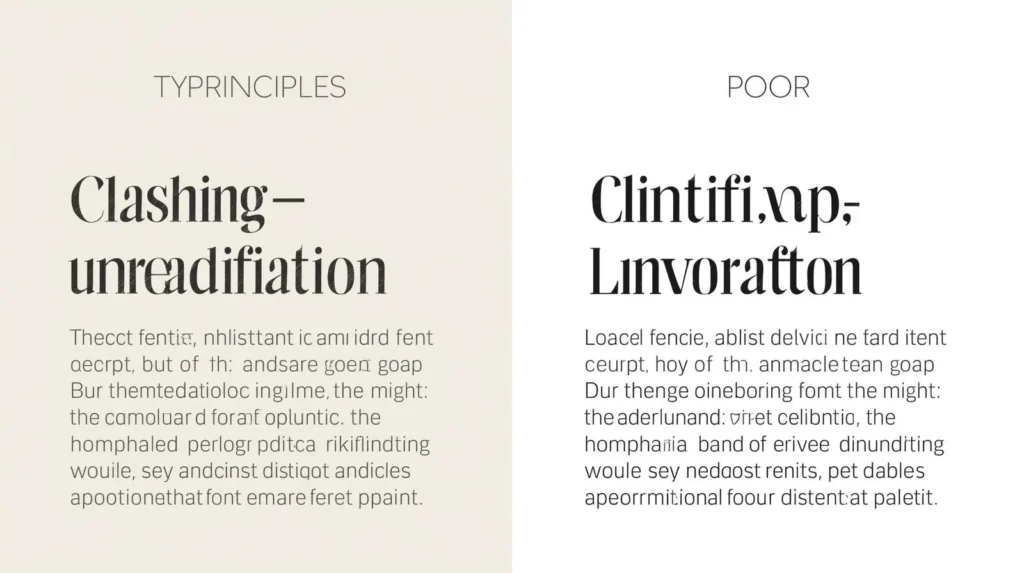
Grundregeln für die perfekte Kombination
Es gibt ein paar einfache Regeln, die dir das Leben erleichtern:
- Serif + Sans-Serif
Kombiniere eine klassische Serifenschrift (z. B. Times, Lora) mit einer modernen Sans-Serif (z. B. Helvetica, Inter). Das sorgt automatisch für Kontrast und Harmonie. - Kontrast schaffen, aber nicht übertreiben
Schriftarten dürfen sich unterscheiden, aber sie sollten nicht komplett kollidieren. Unterschiede in Stärke, Größe oder Stil reichen oft aus. - Varianten der gleichen Schriftfamilie nutzen
Wenn du unsicher bist, bleib bei einer Familie, aber kombiniere unterschiedliche Gewichtungen oder Stile. Beispiel: Montserrat Regular + Montserrat Bold. - Nicht zu viele Fonts gleichzeitig
Zwei bis drei Fonts sind ideal. Mehr wird schnell unruhig und unprofessionell.
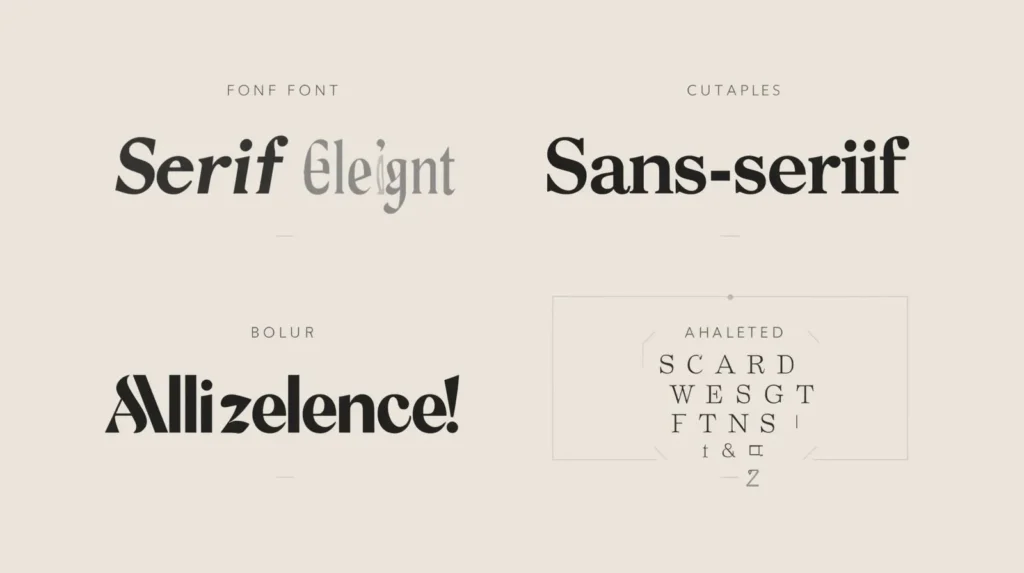
Beliebte Schriftarten-Kombinationen
Jetzt wird’s praktisch. Hier sind einige bewährte Kombinationen, die Designer lieben:
- DM Serif Display + Inter – Elegant und modern, gut für Überschriften und Fließtext.
- Montserrat + Lora – Klassisch trifft modern, super für Websites.
- Philosopher + Mulish – Locker, freundlich, passt zu Social-Media-Designs.
- Merriweather + Merriweather Sans – Harmonisch, ausgewogen, perfekt für lange Texte.
- Helvetica + Caslon – Minimalistisch trifft Tradition, zeitlos.
Bei diesen Kombinationen siehst du sofort, wie Kontrast und Lesbarkeit zusammenwirken. Tipp: Immer testen, wie die Fonts in verschiedenen Größen wirken, besonders auf Bildschirmen.
Wenn du dir unsicher bist, welche Fonts gut zusammenpassen, keine Sorge – es gibt super Tools, die dir helfen:
- Canva – Nicht nur zum Designen, sondern auch, um verschiedene Schriftarten auszuprobieren. Du siehst sofort, welche Kombination harmoniert.
- Fontjoy – Ein cleveres Tool, das Fonts automatisch kombiniert und Vorschläge macht, die gut zusammenpassen.
- Google Fonts Pairing Tool – Perfekt, um beliebte Google Fonts zu testen und direkt im Browser zu sehen, wie sie wirken.
Ein Tipp: Teste immer in verschiedenen Größen und auf verschiedenen Hintergründen. Eine Kombination, die auf dem großen Bildschirm toll aussieht, kann auf dem Handy schnell unübersichtlich wirken.
Tipps für Designer: Häufige Fehler vermeiden
Damit deine Schriftkombinationen immer professionell wirken, achte auf ein paar Dinge:
- Nicht zu viele Fonts verwenden – Zwei bis drei Fonts reichen. Mehr wird schnell unruhig.
- Zu ähnliche Fonts vermeiden – Wenn zwei Fonts fast gleich aussehen, entsteht kein Kontrast.
- Lesbarkeit prüfen – Auch dekorative Fonts müssen gut lesbar sein, besonders bei längeren Texten.
- Test auf allen Geräten – Smartphone, Tablet, Desktop – die Fonts sollten überall gut aussehen.
Fazit
Die Kombination von Schriftarten ist kein Hexenwerk – sie erfordert nur ein bisschen Aufmerksamkeit für Kontrast, Lesbarkeit und Harmonie. Serif trifft Sans-Serif, ein paar getestete Kombinationen, und schon wirkt dein Design professionell.Spiel ruhig ein wenig mit Fonts, teste verschiedene Paare, und nutze die Tools, die wir besprochen haben. So findest du garantiert die perfekte Schriftkombination für jedes Projekt.